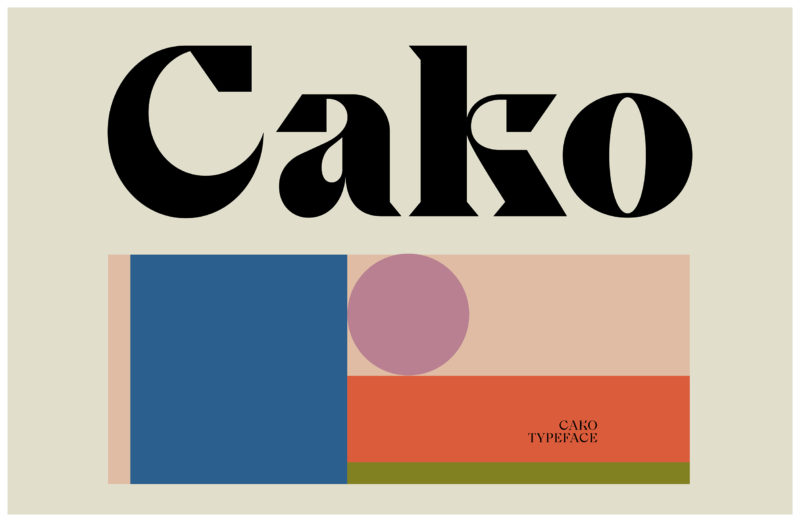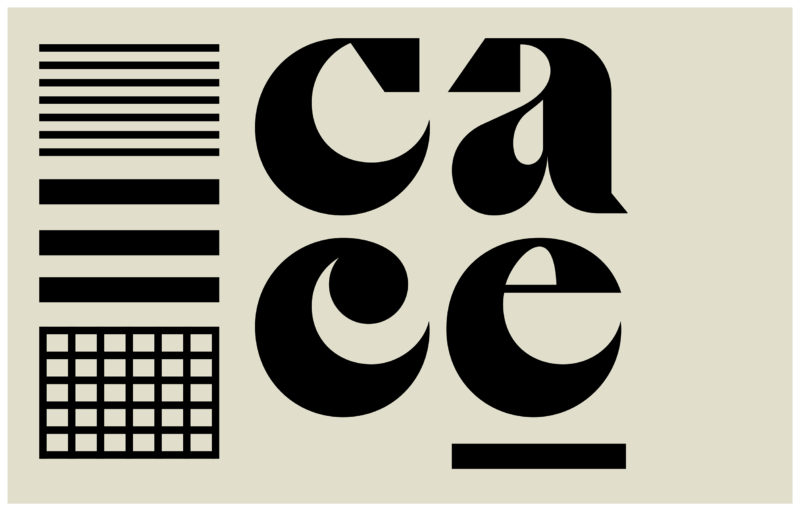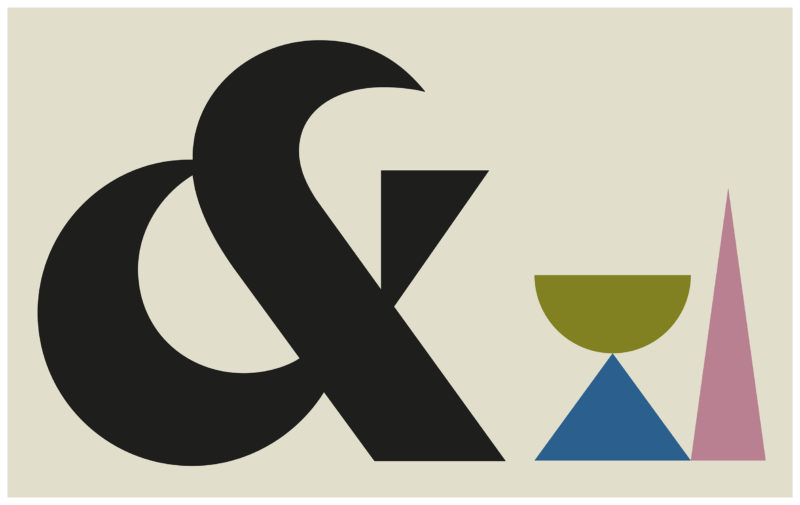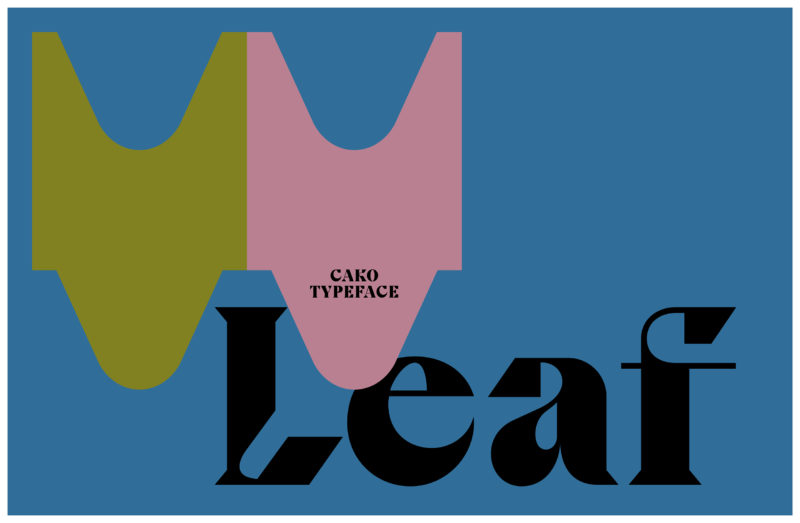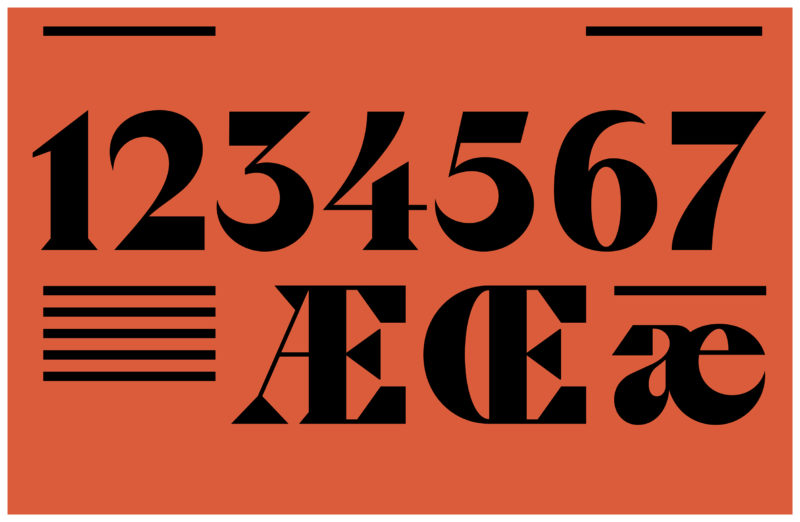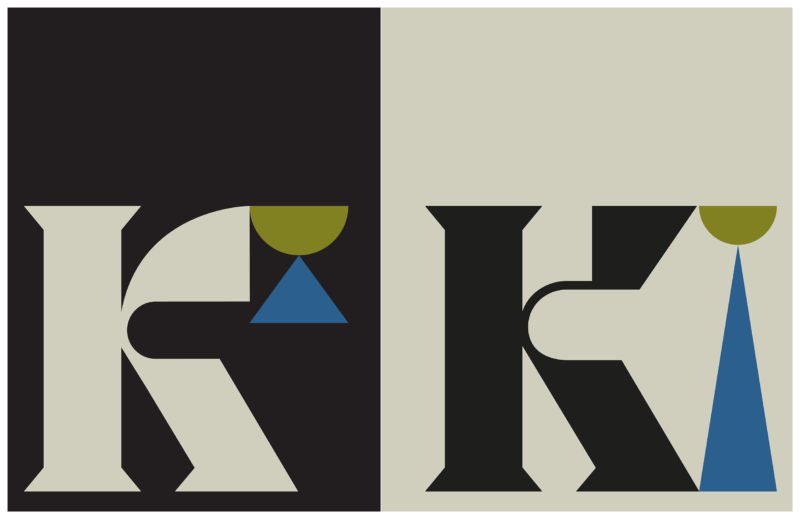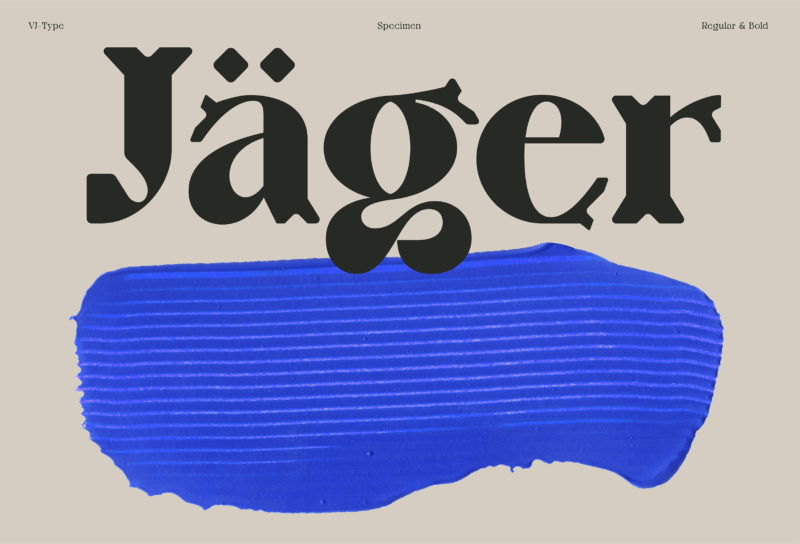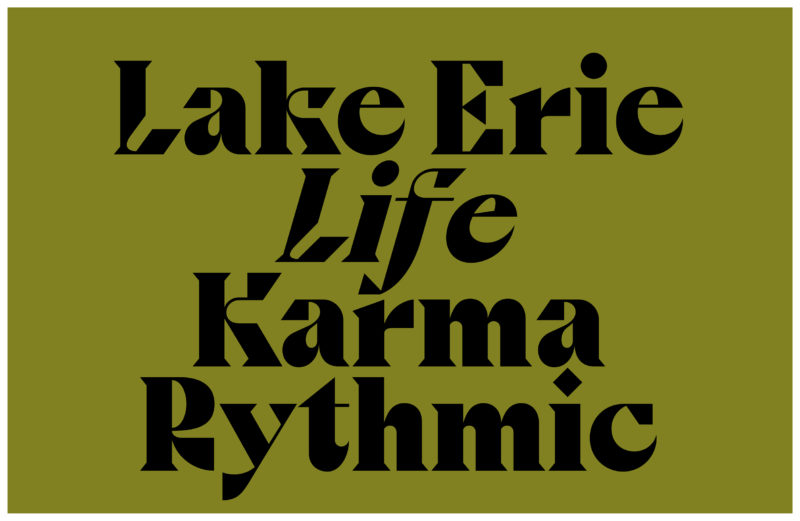
Más francesas imposible
El caso de VJ Type es realmente curioso, se trata de una fundición que nace del éxito comercial y profesional de Violaine & Jérémy, aquel delicioso estudio parisino que desde 2012 y de la mano de sus fundadores: Violaine Orsoni y Jérémy Schneider, viene maravillando al mundo del diseño un día sí y otro también.
Como no podía ser de otra manera, la propuesta VJ Type se inspira y se alimenta del acervo de Violaine & Jérémy y el resultado no podía ser mejor. Para muestras un botón, o en este caso, tres.
En primer lugar tenemos a Cako, una de sus creaciones más antiguas. Robusta si se necesita dar un golpe sobre la mesa, delicada si lo suyo es insinuar. Versátil como nadie, «Cako se caracteriza por sus grandes contrastes, trazos gruesos y delgados, detalles finos y remates agudos», comenta Schneider.
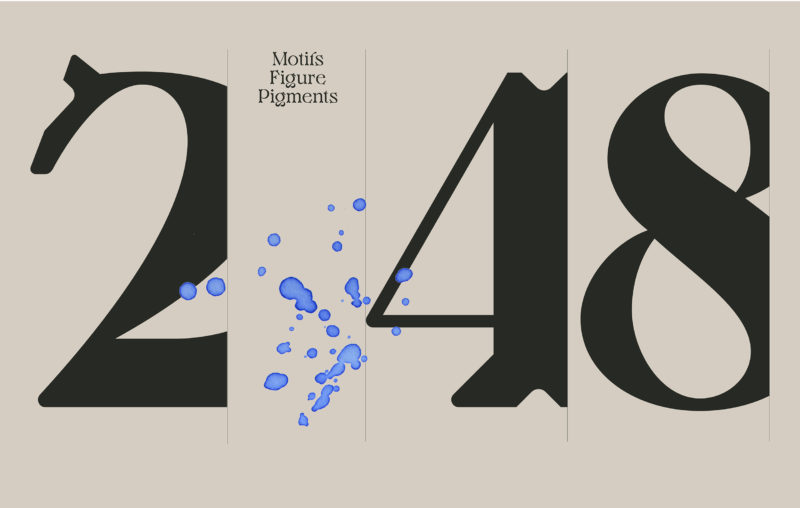
Jäger por otra parte es una tipografía de exhibición, útil para titulares o textos cortos o medianos. Presentada en 2020, su desarrollo comenzó cinco años antes, en una exposición dedicada al arte contemporáneo y la artesanía en el Museo de las Artes Decorativas de París. «Jäger es un tributo a la artesanía fina. Esta fuente está inspirada en técnicas de construcción artesanales. Podemos ver formas que recuerdan a grabados, esculturas o trabajo con cinceles», comenta Schneider y agrega: «Sus ángulos dan la impresión de haber sido tallados en madera, los contornos son redondeados, nunca afilados. Cada peso ofrece dos versiones: la versión Jäger Master, que es el diseño original, más avanzado y atrevido, y la versión Jäger Classic, en la cual se han rellenado las formas de contra en la parte superior de las letras para ofrecer una opción más suave y versátil».
En último lugar y no por eso menos importante, tenemos a Eros, una familia arrolladora nacida de la fusión de dos tipografías personalizadas que Orsoni y Schneider dieron vida recientemente para Le Théâtre des Bouffes du Nord de París y un proyecto exclusivo realizado junto a Pharrell Williams y Jean Imbert en Saint-Tropez. «La estética de Eros está inspirada en el movimiento artístico Jugendstil y la Secesión vienesa de finales del siglo XIX, y se rediseñó con un toque contemporáneo que aporta una elegante nitidez al dibujo. Tiene una expresión muy refinada, transmite una hermosa sensación orgánica y, sin embargo, la tipografía sigue siendo funcional. Dibujamos 30 pares de ligaduras en mayúsculas y 30 pares de ligaduras en minúsculas para garantizar las secuencias de palabras más hermosas posibles».
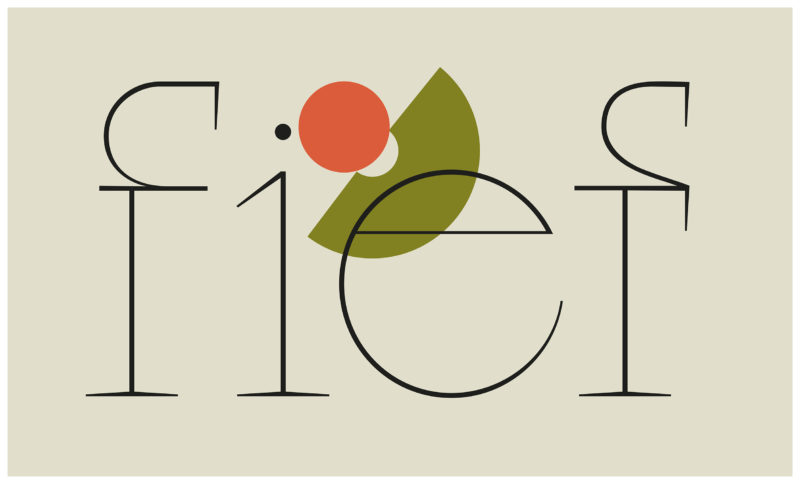
En definitiva, VJ Type es el ejemplo perfecto de las posibilidades que los profesionales de la ilustración tienen en este ámbito. Gente como Jérémy Schneider, ilustrador y artista consumado, ha sabido sacarle un rendimiento superlativo a este binomio ganador. Ojalá estemos ante una veta madre aún por explotar.